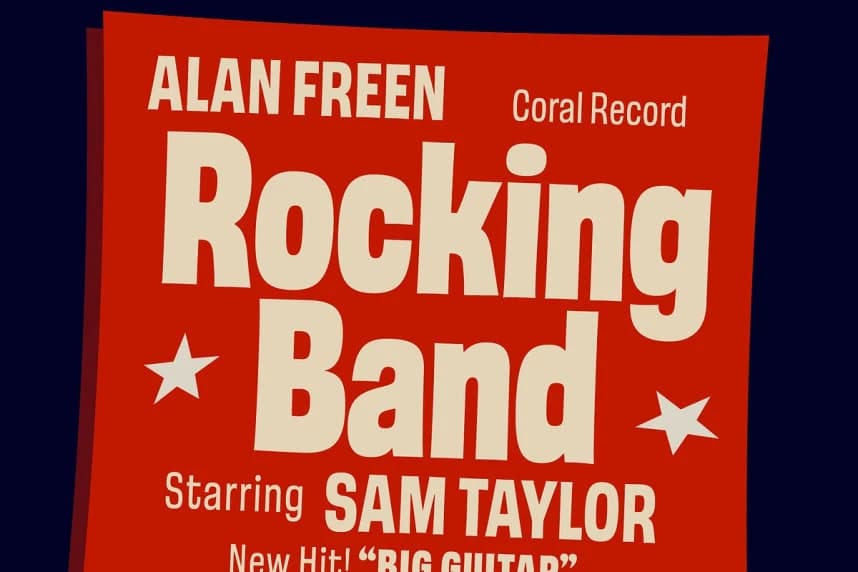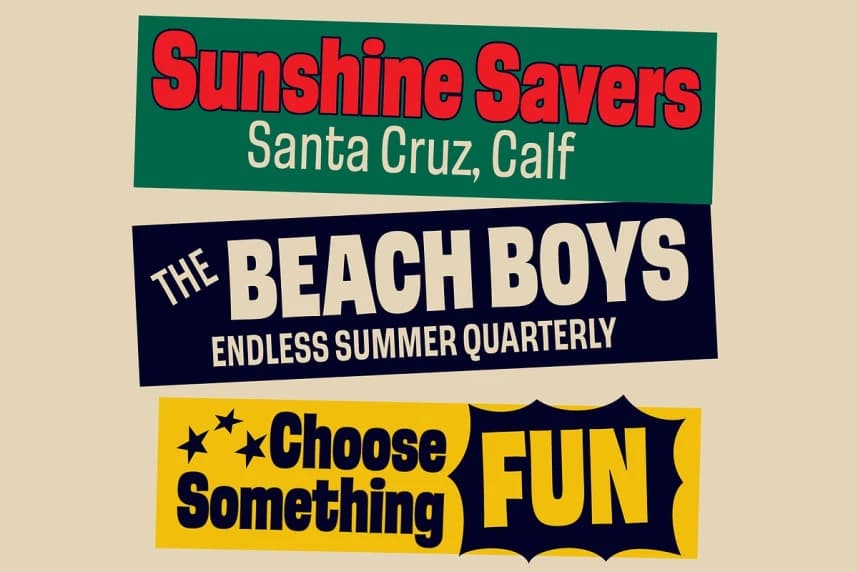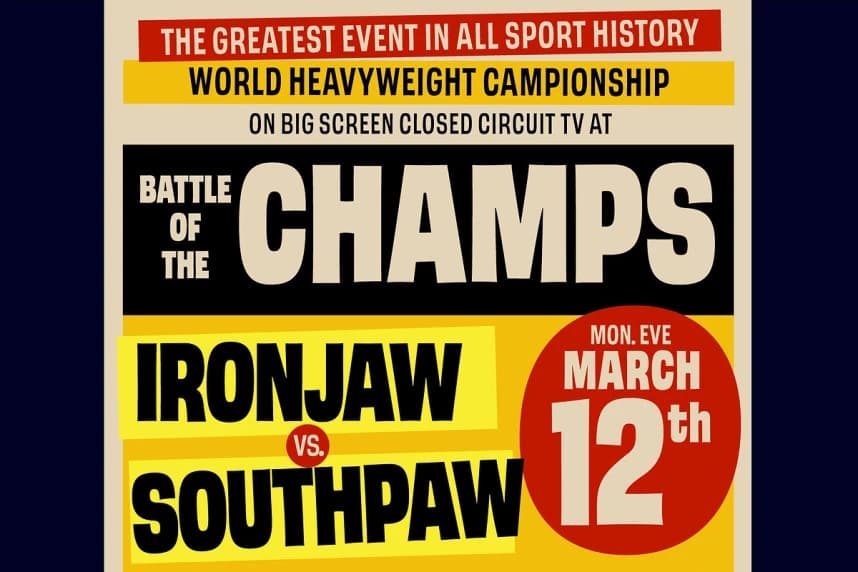
GW Swingstar Font Family, 1960'ların Kaliforniya ruhundan esinlenen dinamik bir gösteri sans-serif font ailesidir—burada sörf kültürü, güneşten solmuş posterler ve kaygısız kıyı yaşamı cesur bir görsel kimlik oluşturmaktadır. Temiz ve modern bir yapıyı ince retro bir karakterle harmanlar.
GW Swingstar Font Family Dinamik bir display sans serif, 1960'ların Kaliforniyasının ruhundan ilham alan—sörf kültürü, güneş solmuş posterler ve kaygısız kıyı yaşamının cesur bir görsel kimlik oluşturduğu yer. Temiz, modern bir yapıyı ince retro bir karakterle harmanlar.